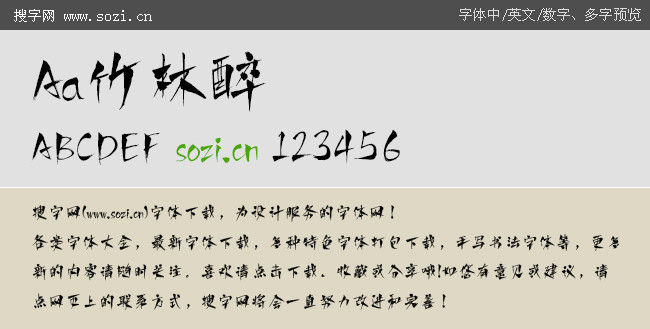
Aa竹林醉
搜字網(wǎng)給大家提供一款A(yù)a竹林醉(非商業(yè)使用)中文字體下載,該字體是一款手寫風(fēng)格中文字體, 帶有毛筆飛白效果, 字體工整簡潔, 具有強(qiáng)烈的視覺沖擊力, 適合包裝設(shè)計、書裝設(shè)計、海報設(shè)計等應(yīng)用(此字體為個人非商用版,商用可以聯(lián)系QQ:1006760504)。